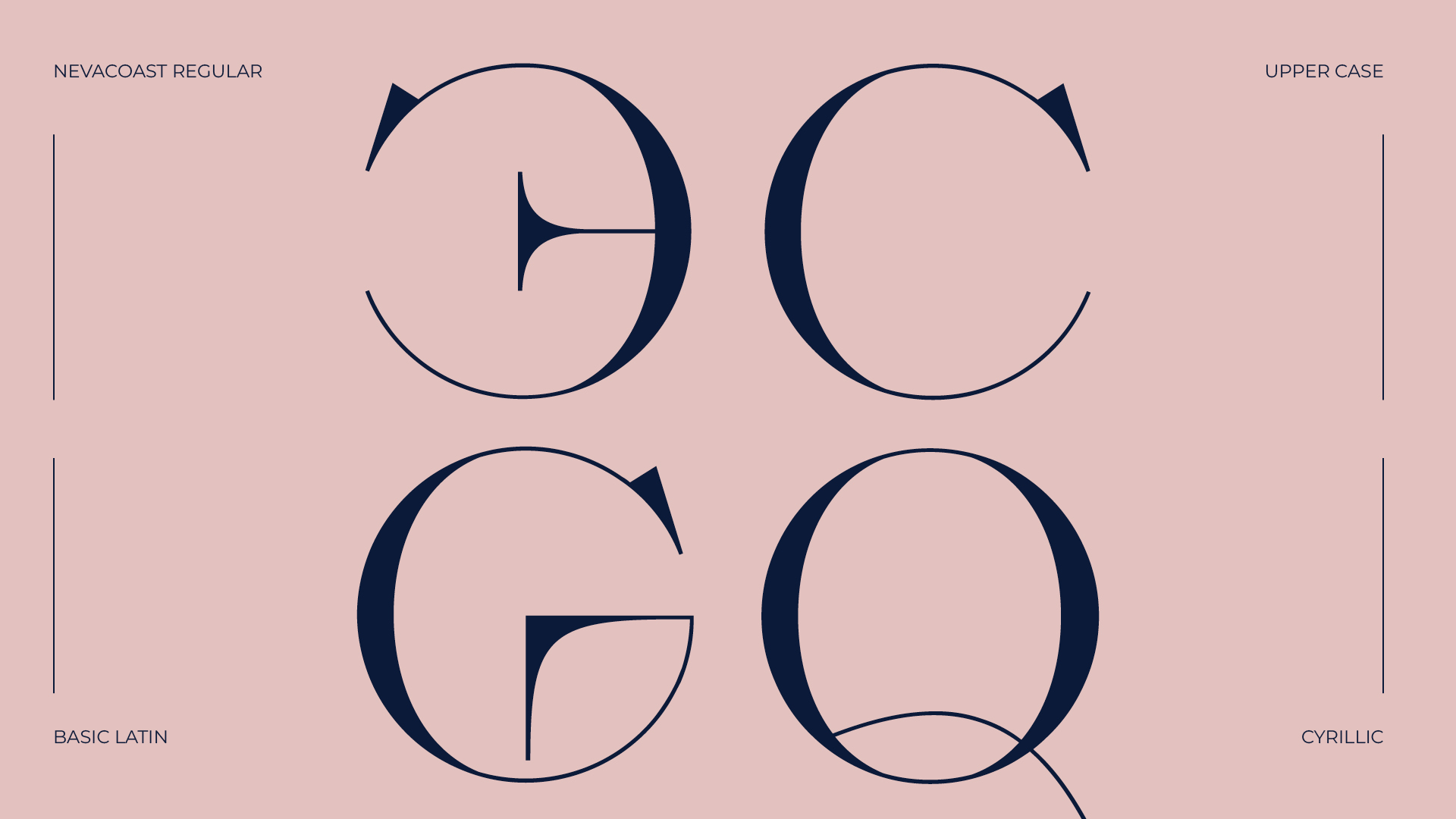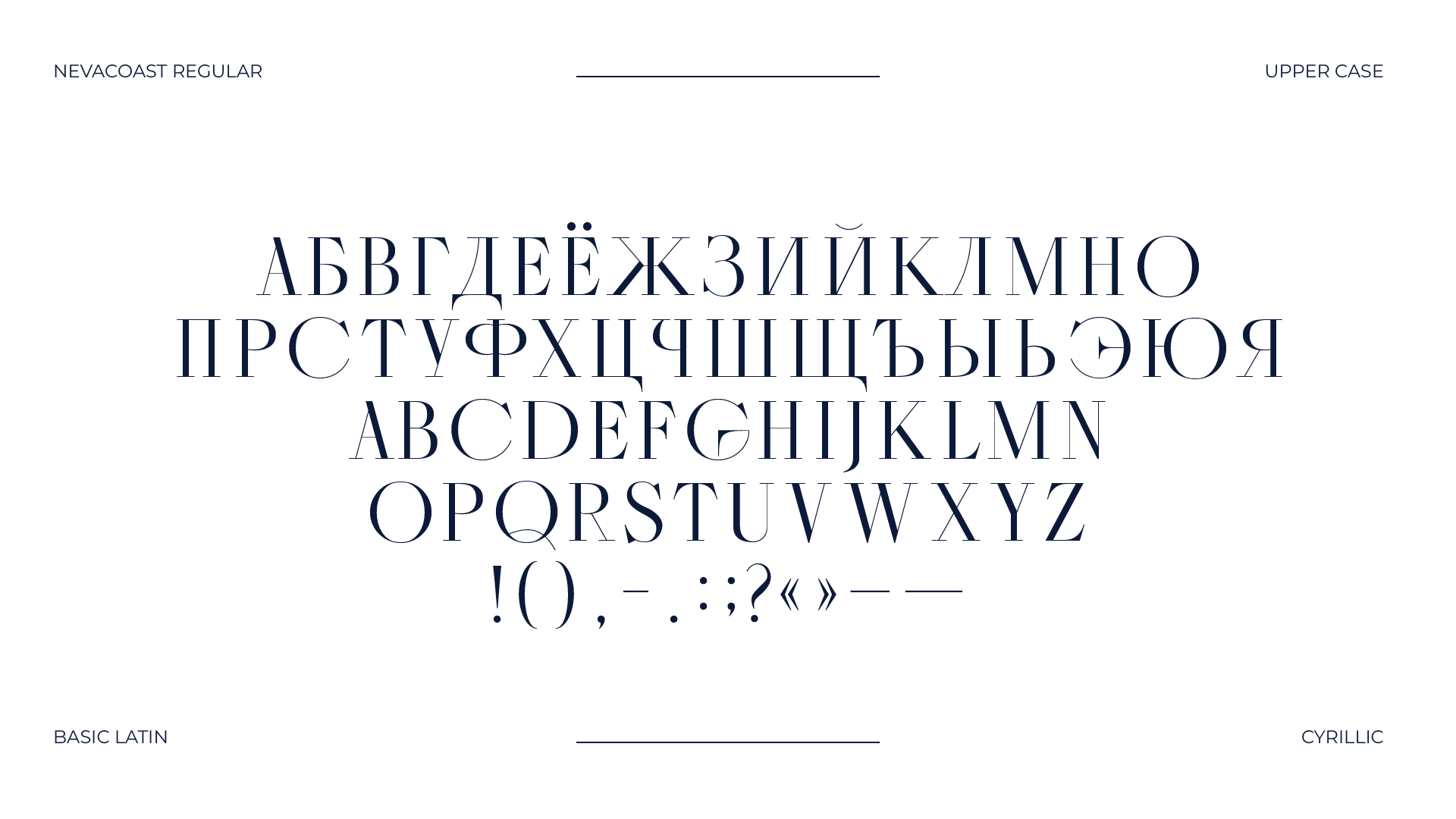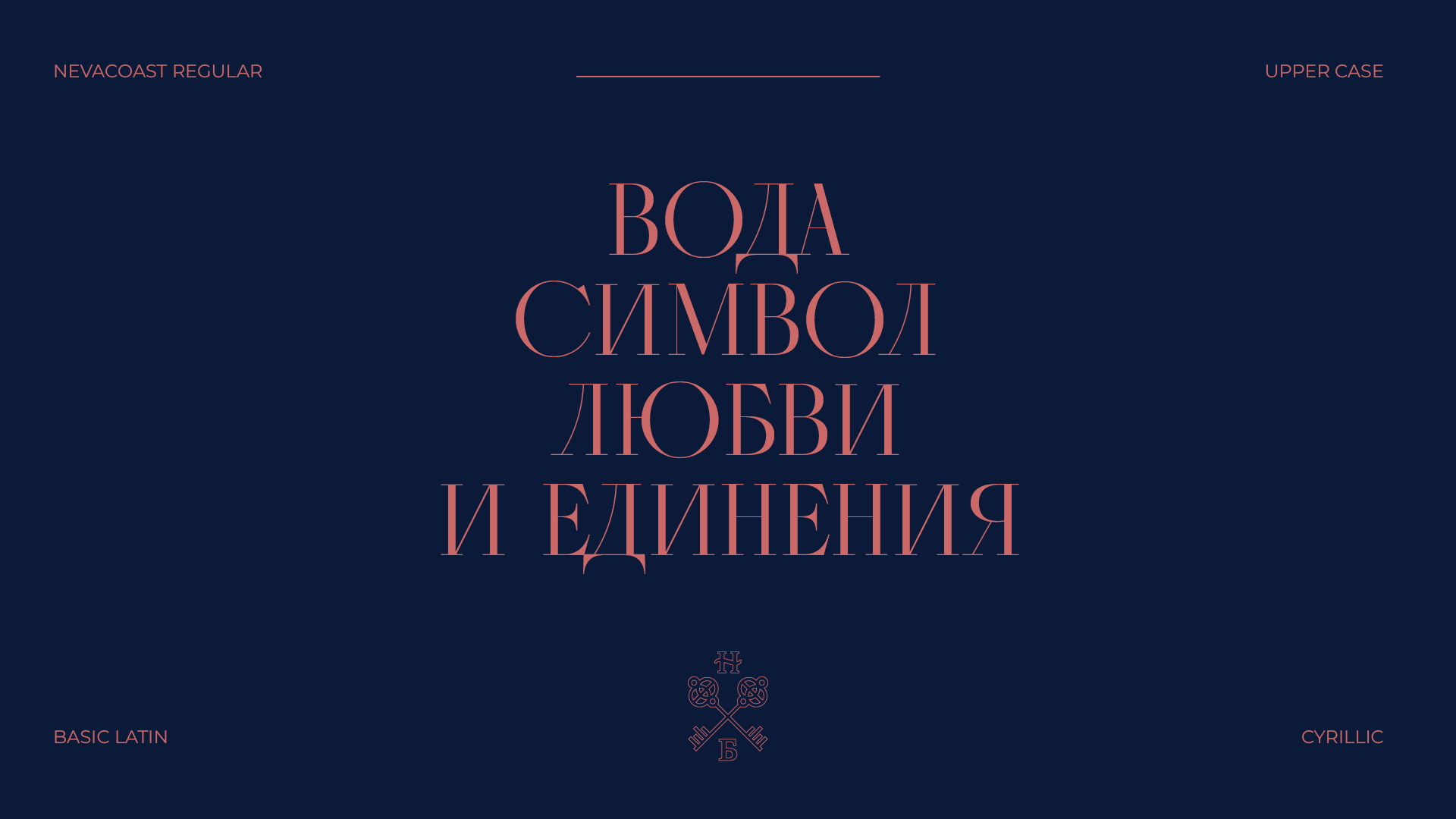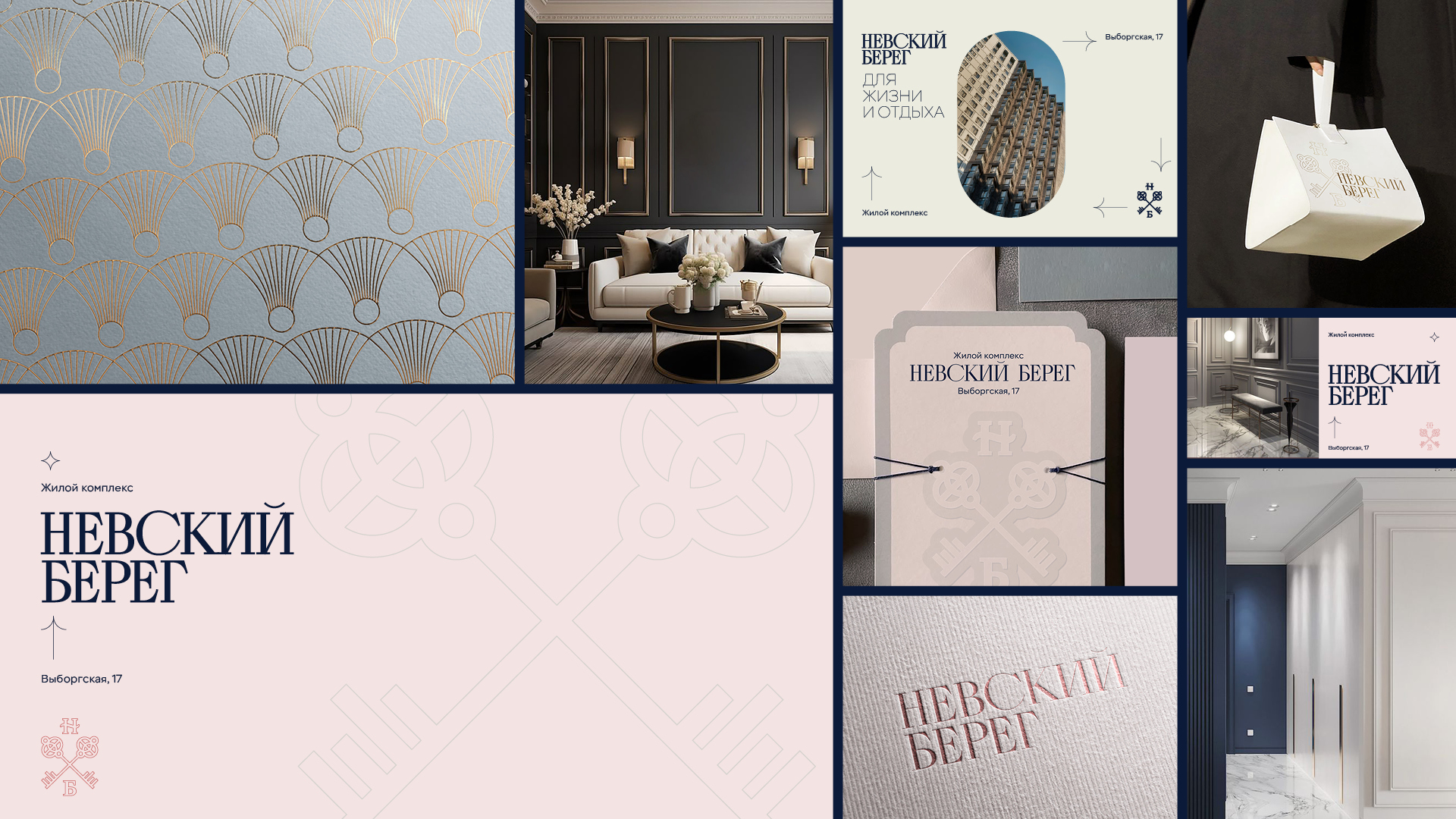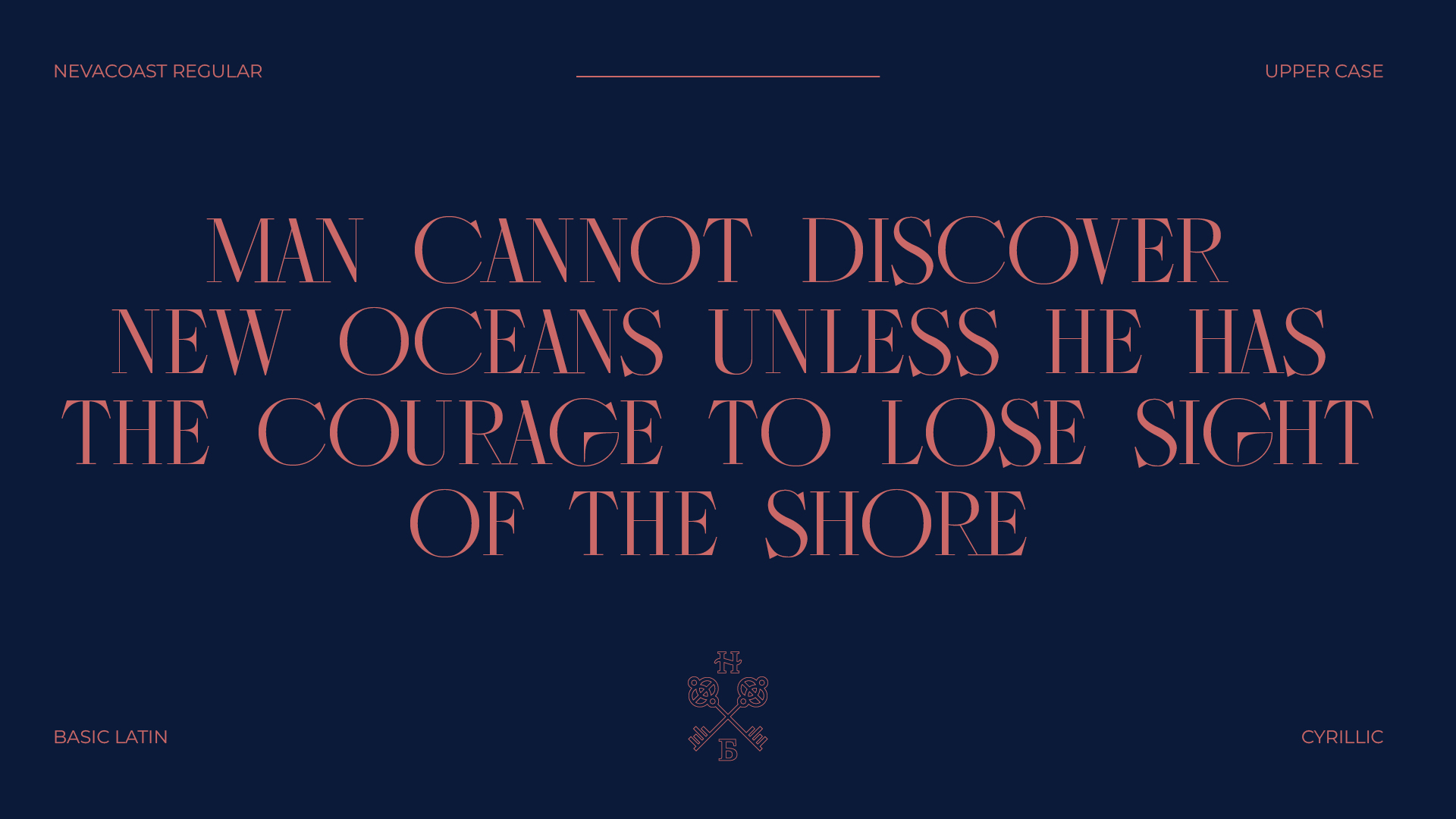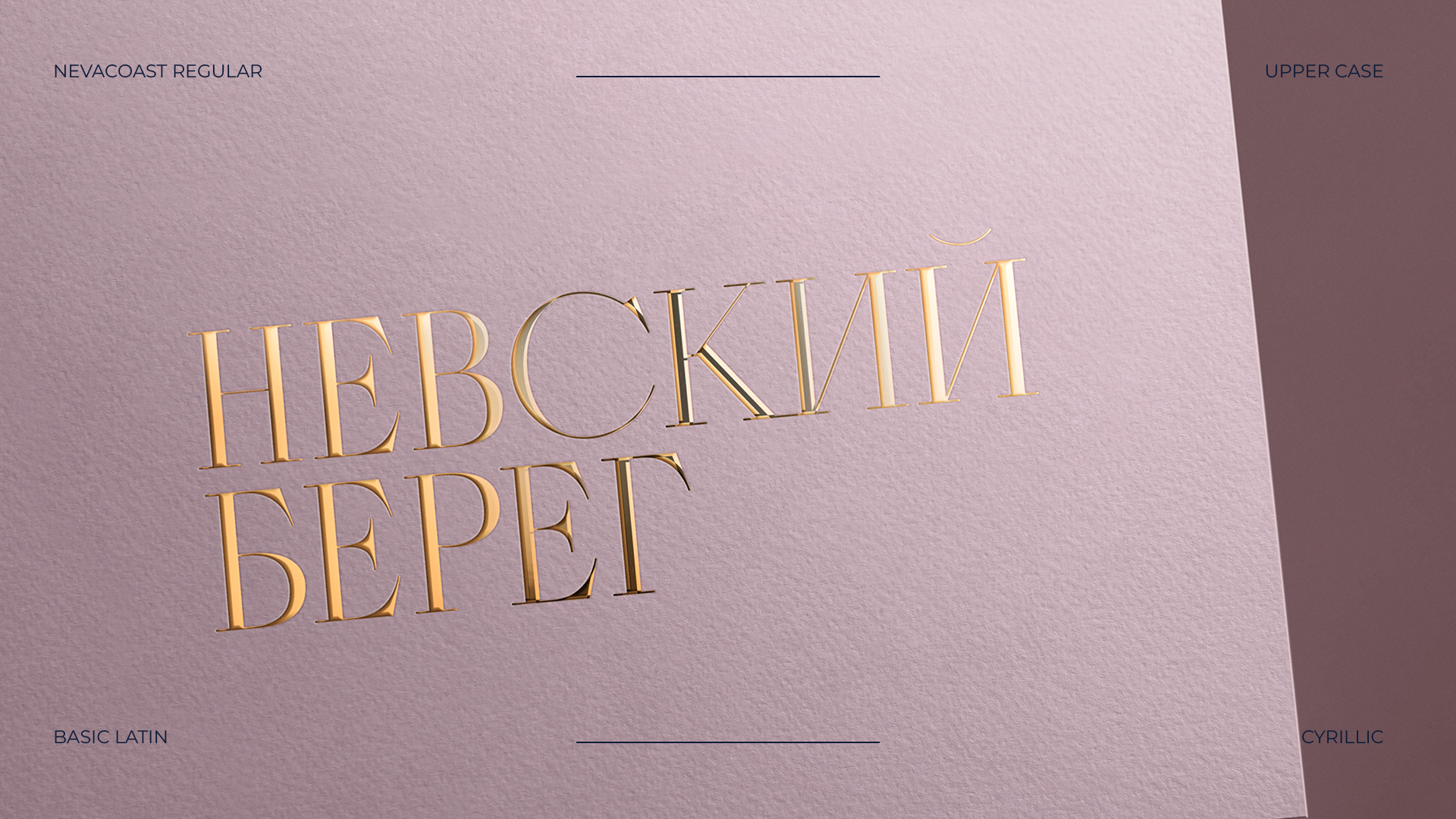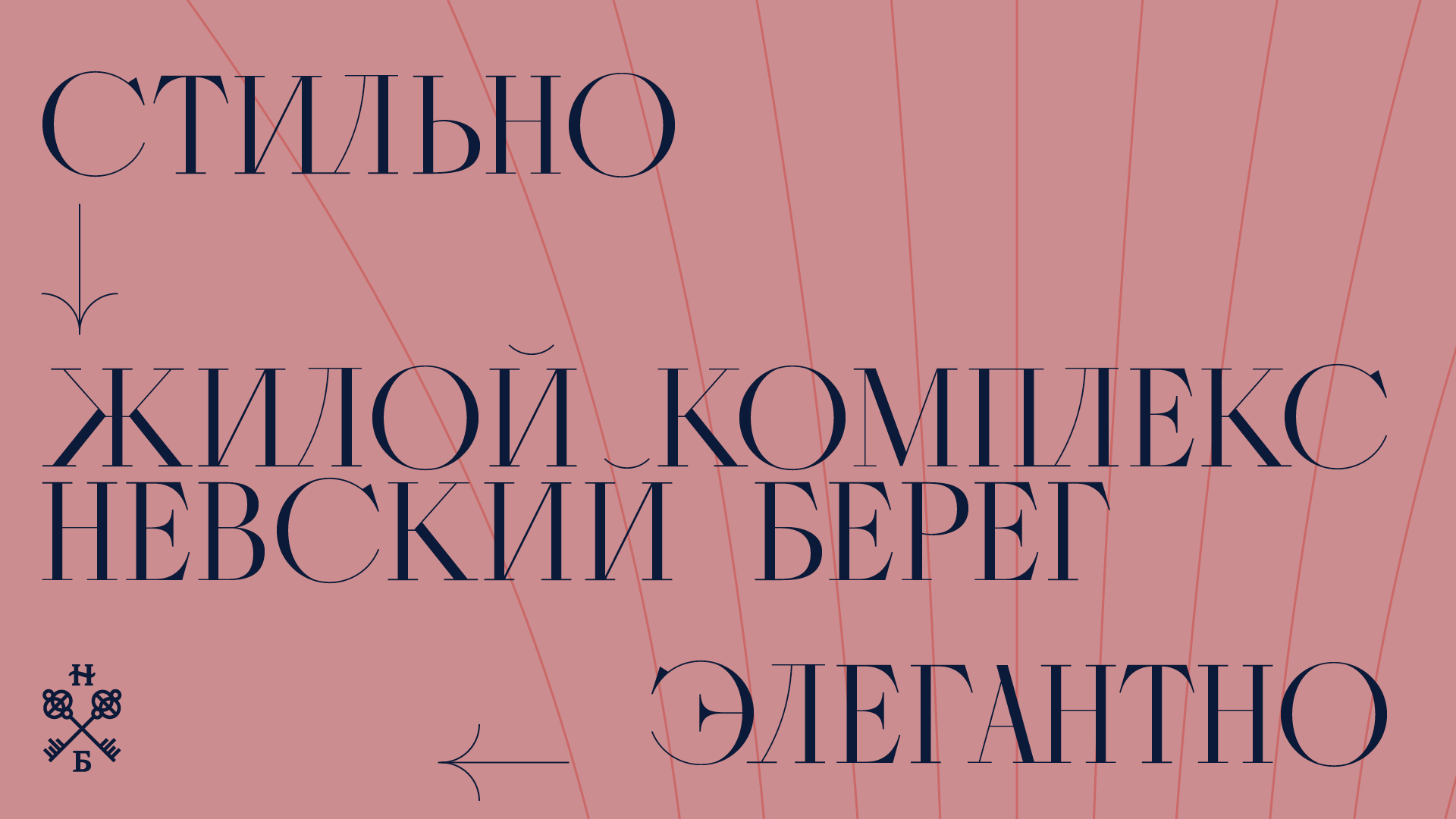
Nevacoast
Шрифт Nevacoast был разработан специально под проект для айдентики ЖК «НЕВСКИЙ БЕРЕГ» концерна КРОСТ. Стилистика шрифта лежит в плоскости утончённых новых антикв в стиле шрифтов работ великих дизайнеров Джамбаттисты Бодони и Фирмена Дидо. Кажется, что все шрифтовые дизайнеры рано или поздно обращаются к столь утончённой шрифтовой теме. Моя задача заключалась в том, чтобы сформировать образ утончённости и лёгкости. На данный момент разработаны только прописные знаки. В дальнейшем будет продолжена работа над строчными знаками.